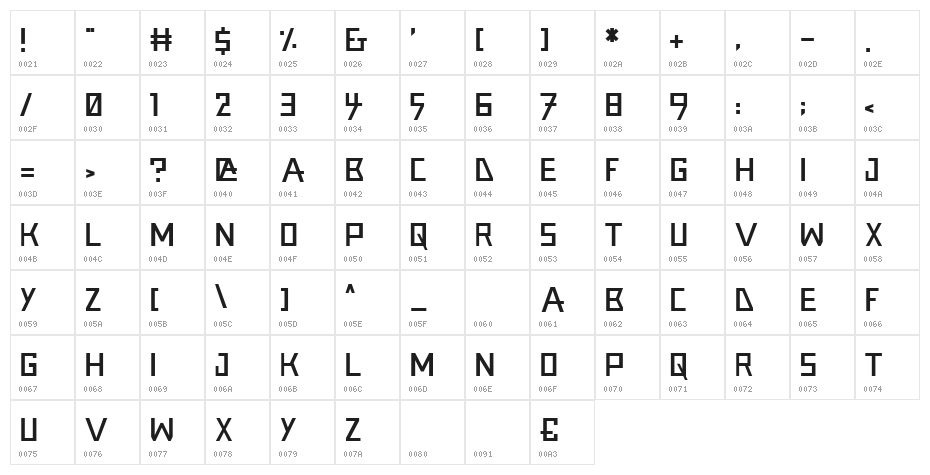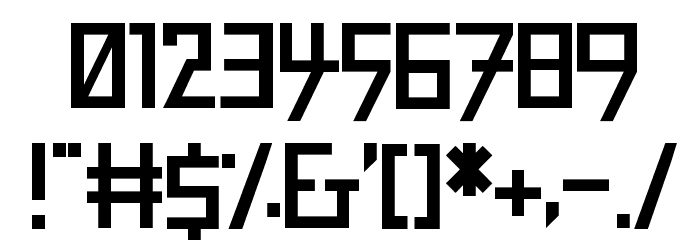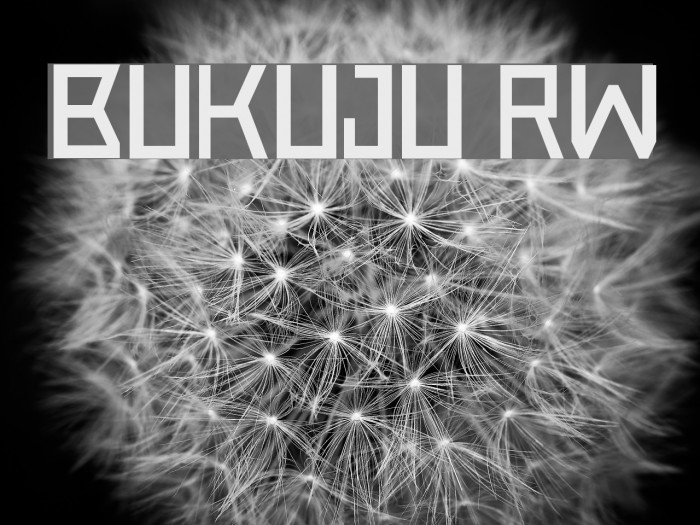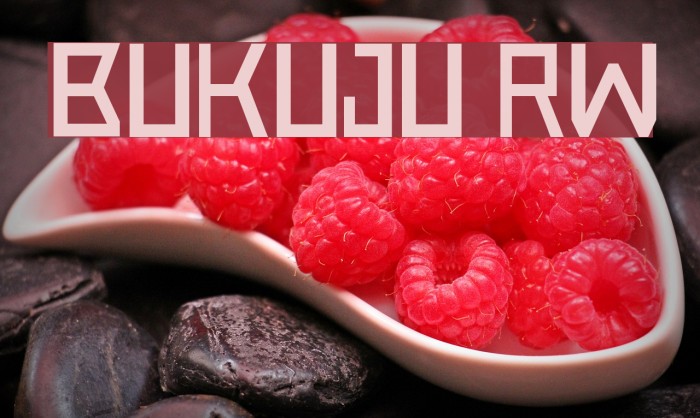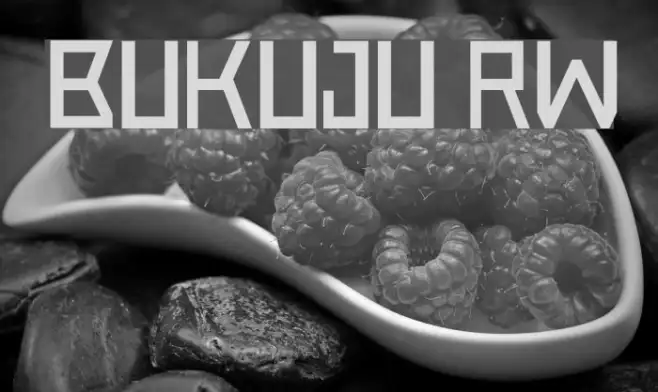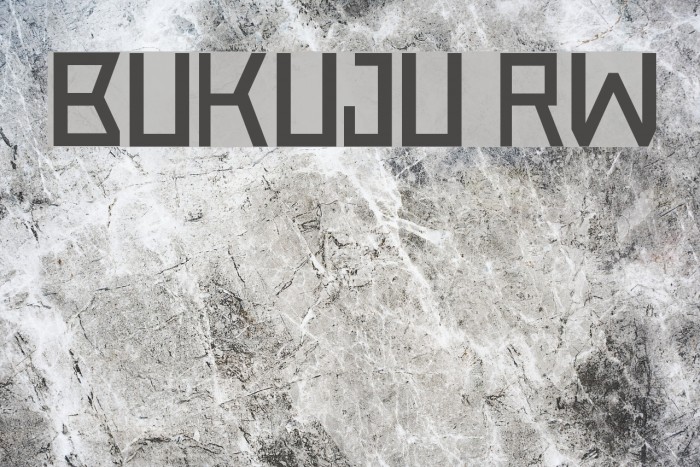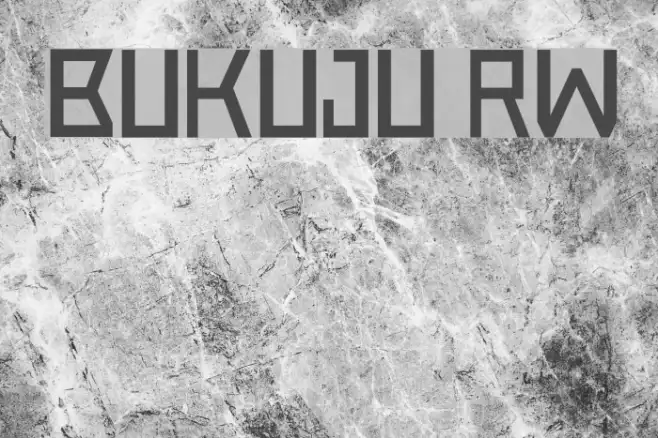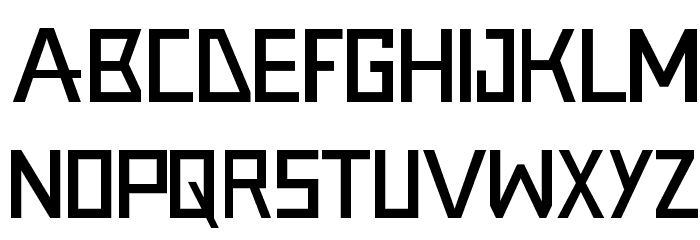
Bukuju RW Font
✎ Futuristic
| Vorgeschlagene Projekte | Ideal for technology branding, sci-fi themed projects, modern posters, and digital interfaces. |